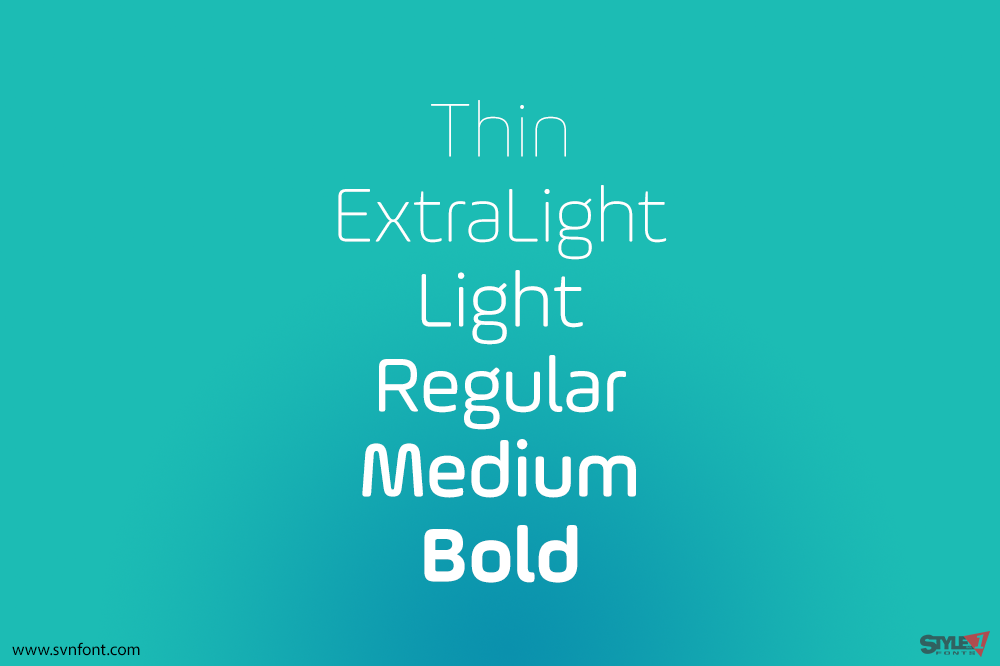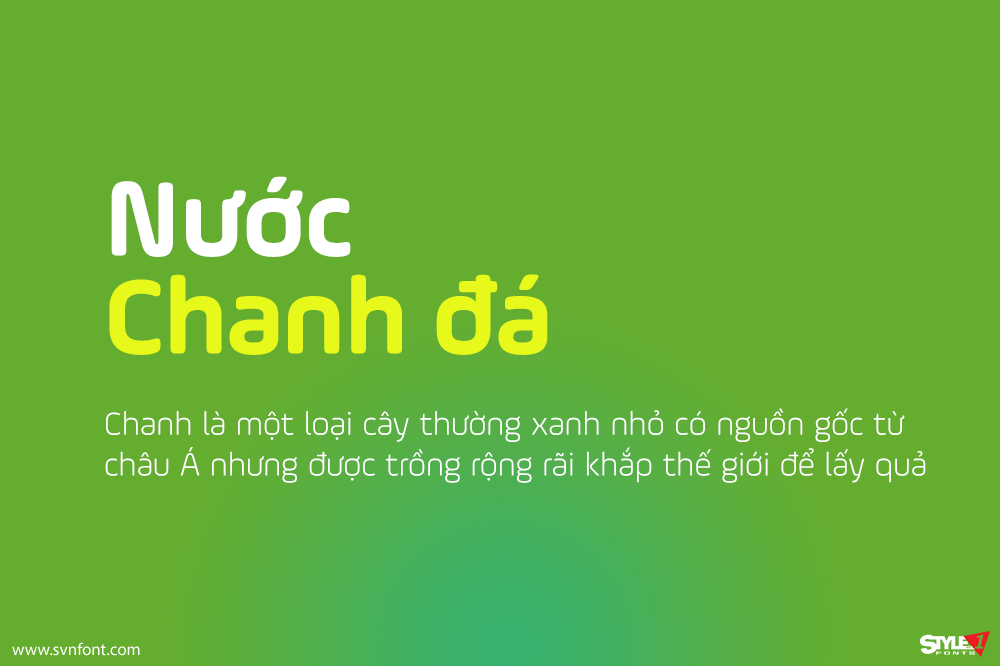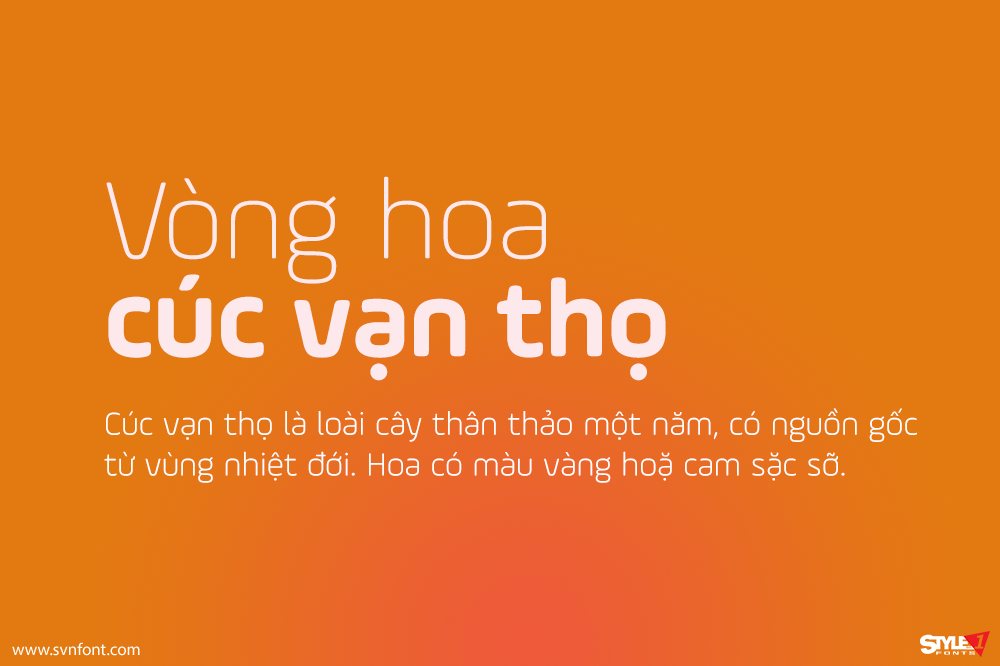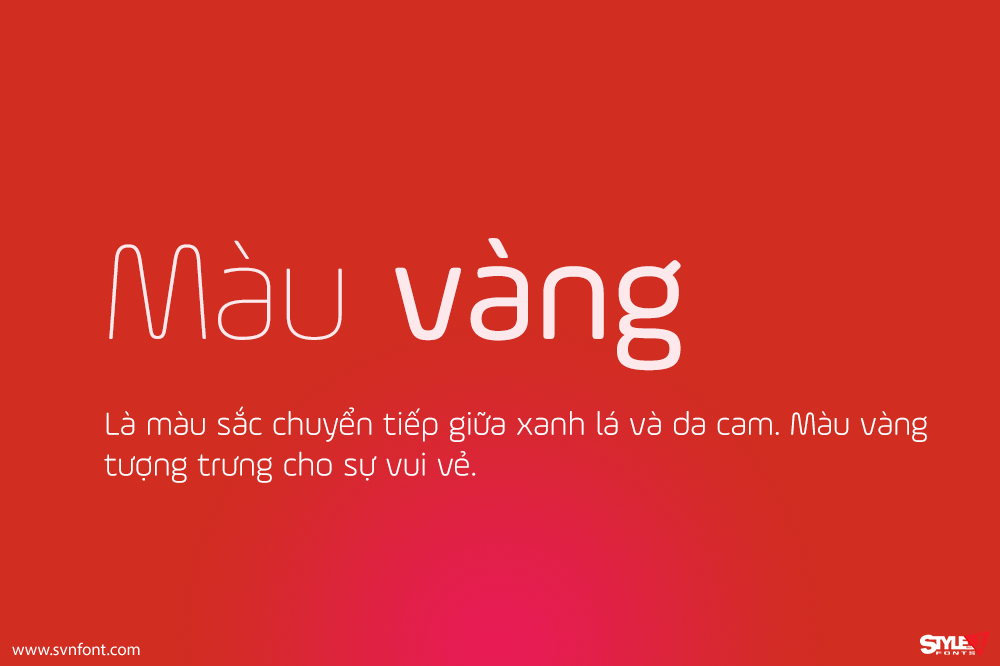
Ample Soft là một phiên bản mềm mại hơn được phát triển từ họ kiểu chữ Ample. AmpleSoft là một họ kiểu chữ hiển thị, có độ đơn tuyến quang học và hơi vuông vức về bản chất. Nó có những đường cong mượt mà thay vì các góc sắc nét được hình thành từ chỗ nối của hai nét, đây là một đặc điểm nổi bật trong thiết kế của nó.
Kiểu chữ này được thiết kế để hơi bắt mắt nhưng vẫn dễ đọc. Nó có các hình dạng chữ cái rõ ràng và dễ phân biệt, giúp làm rõ và nhấn mạnh thông điệp. Về mặt đồ họa, nó mạnh mẽ và thu hút sự chú ý của người xem. Tổng thể kiểu chữ phù hợp để đặt làm tiêu đề, tựa đề, headline, v.v.
Họ kiểu chữ này bao gồm sáu độ đậm: Thin, ExLight, Light, Regular, Medium và Bold. Xét về bản chất của họ kiểu chữ này, các kiểu in nghiêng đã được loại trừ.